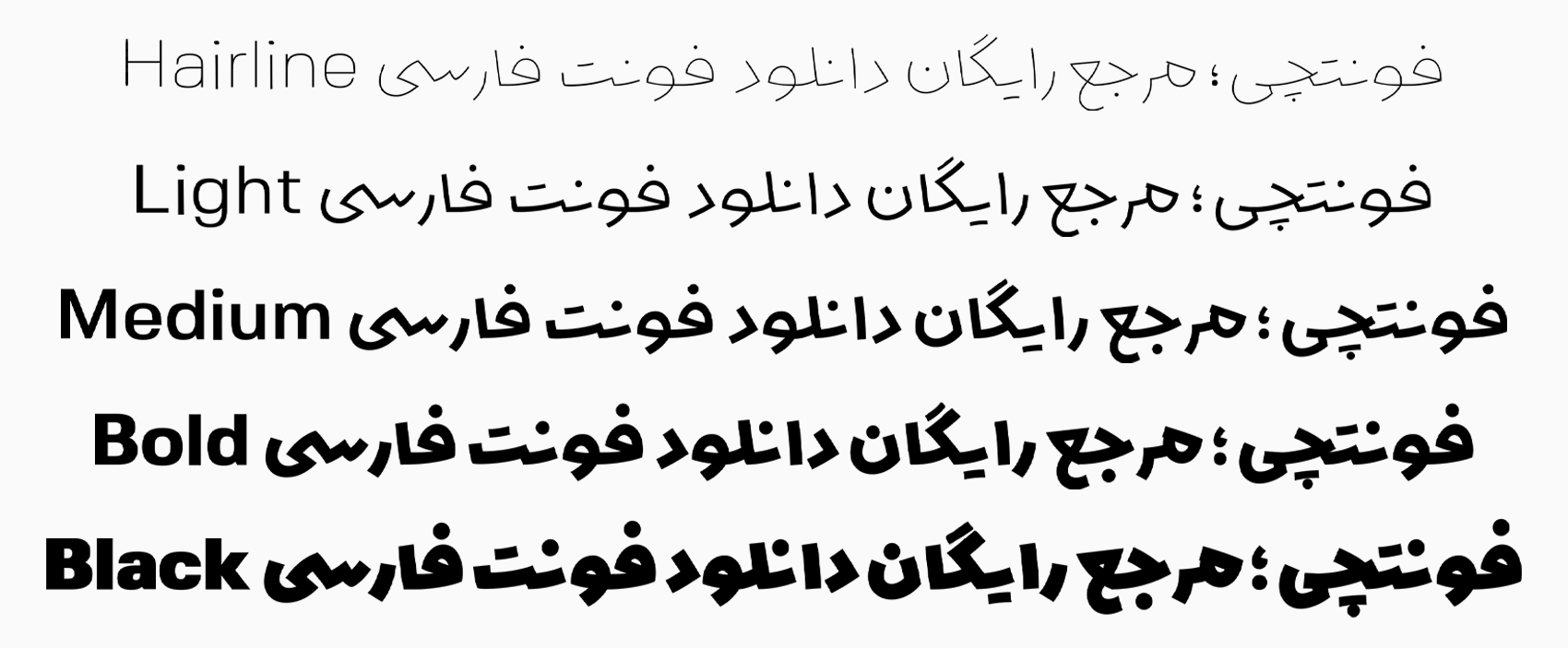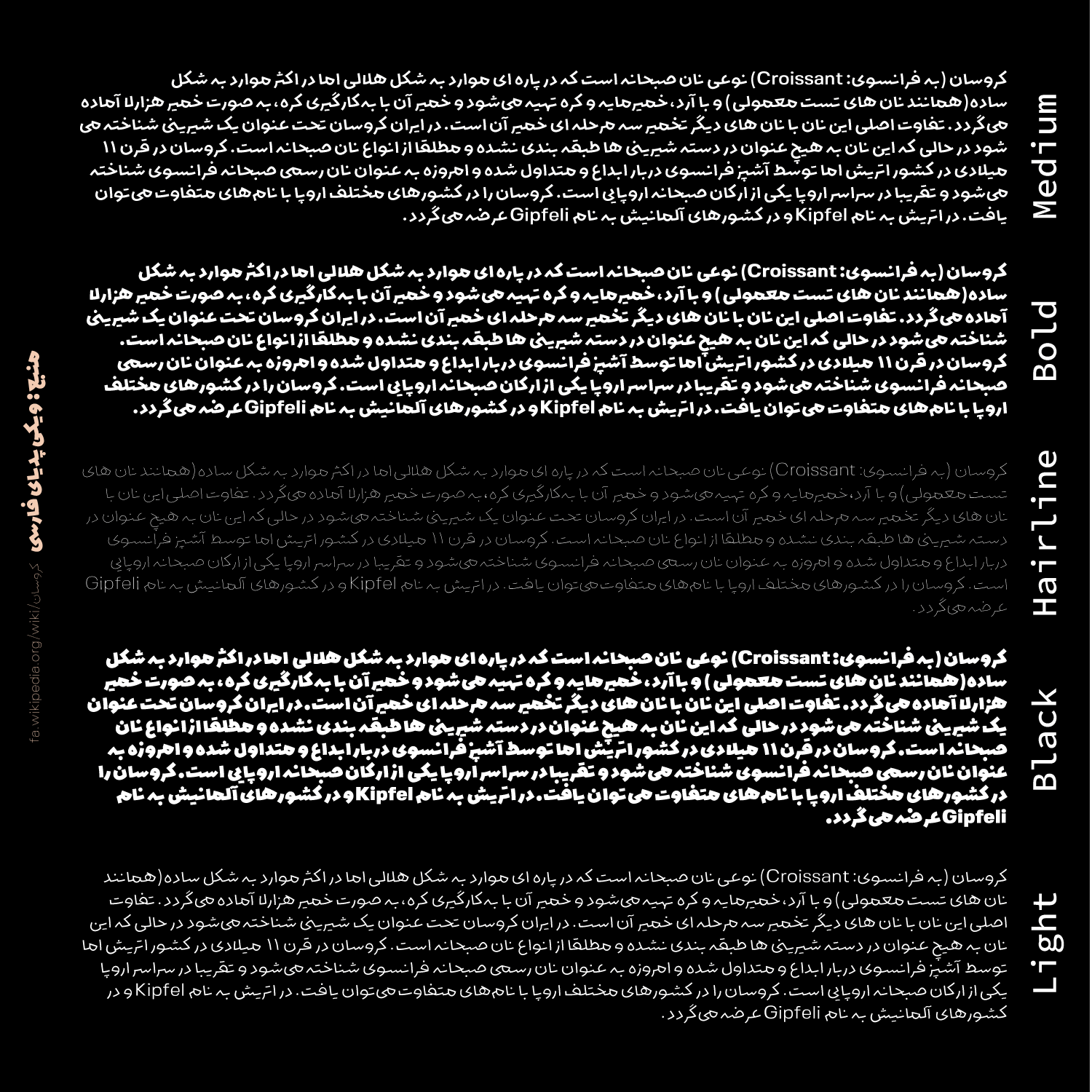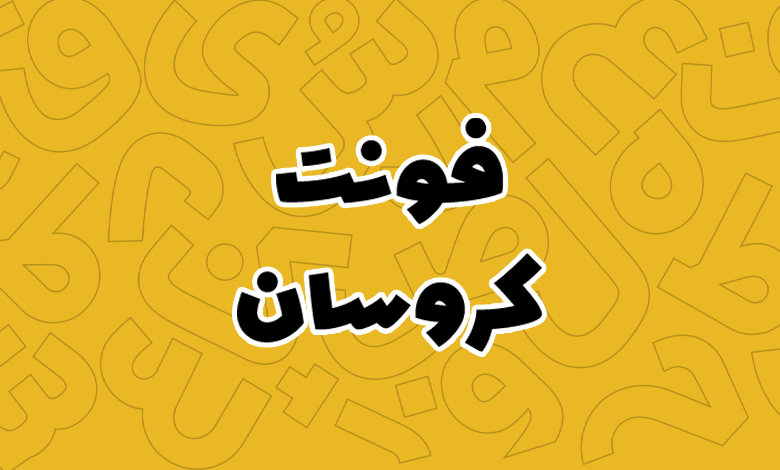
فونت کروسان (Croissant)
فونت کروسان (به انگلیسی: Croissant) از فونتهای جذاب و مدرن جدید با ساختاری هندسی است که با طراحی منحصربهفرد خود میتواند گزینهای ایدهآل برای استفاده در پروژههای متنوعی که با هدف فونت عناوین، بستهبندی محصولات و تبلیغات به آن نیاز داشته باشید مورد استفاده قرار گیرد. فونت کروسان رایگان نیست و در ۵ وزن مختلف در قالب دو بسته نرمافزاری ارائه شده است.
طراح فونت کروسان علی پزشک است که پیش از این فونت سینما را در سال ۱۳۹۵ طراحی نموده است. فونت کروسان نیز با همان سبک کلاسیک و قدیمی این خط طراحی شده است که در ادامه بیشتر به بررسی و معرفی این قلم خواهیم پرداخت.
بررسی و دانلود فونت کروسان فارسی (croissant)
فونت کروسان (Croissant) یک فونت چندمنظوره با طراحی مدرن و هندسی است که توانسته تعادلی زیبا میان سنت و نوآوری ایجاد کند. پشتیبانی از سه زبان، تنوع وزنی و اعداد فارسی حرفهای از جمله ویژگیهایی هستند که این فونت را به گزینهای محبوب برای طراحان تبدیل کردهاند.
ظاهر این فونت کلاسیک بوده و به طراحی حروف پیش از سال ۵۷ برمیگردد که عموما از این سبک فونت برای پوسترهای سینمایی و طراحی تابلوهای سردر واحدهای تجاری مورد استفاده قرار میگرفت.
با توجه به کاربردهای گستردهای که دارد، فونت کروسان یک انتخاب ایدهآل برای پروژههای دیجیتال و تبلیغاتی است که در ادامه بیشتر با آن آشنا خواهیم شد.
سبک طراحی و وزن فونت کروسان
کروسان با بهرهگیری از ساختار هندسی و فرمهای ساده، تعادل بین سنت و مدرنیته را بهزیبایی برقرار کرده است. این فونت در ۵ وزن مختلف ارائه شده که عبارتند از:
- Hairline: مناسب برای طراحیهای ظریف و مینیمال.
- Light: مناسب برای متنهای کوتاه با ظاهری ملایم.
- Medium: وزن تعادلی برای استفادههای عمومی در متون بلند.
- Bold: برای عناوین برجسته و جذاب بین متون بلند.
- Black: قدرتمند و جسور برای استفاده در عناوین همچون پوسترها و کارهای تبلیغات.
تنوع در وزنها، انعطافپذیری بالایی به این فونت بخشیده و آن را برای انواع استفادهها از لوگوتایپ گرفته تا عناوین پوسترها مناسب کرده است.
هر یک از این وزنها شخصیت خاص خود را دارند که برای استفاده در محیطهای مختلف ذکر شده میتواند این خط ره بهشکل ویژهای نمایش دهد. تمامی وزنهای پنجگانه این قلم با فرمتهای TTF, WOFF و WOFF2 ارائه شده که برای استفاده در انواع نرمافزار و فضای وب قابل استفاده است.
پشتیبانی از ۳ زبان متنوع
به لطف فارسی بودن فونت کروسان، این قلم برای استفاده در سایر زبانهای خاورمیانهای همچون عربی نیز قابل استفاده است. با اینکه تمرکز در نسخههای اولیه جدا از زبان فارسی روی عربی است، اما میتوانید برای سایر زبانها همچون کوردی و اردو که دارای ظاهر یکسان در حروف هستند نیز از این خط بهره ببرید.
این فونت با چینش استاندارد اعراب و نشانهگذاری روی حروف، جان تازهای به واژههای شما خواهد بخشید. بهخصوص در وزنهای بالا که در عناوین مورد استفاده قرار گیرد و با هدف تمرکز روی محیطهای تبلیغاتی، نگاه بیننده را بقاپد.
فونت انگلیسی croissant دیگر زبان پشتیبانی شده این خط است که روح دورانی فرهنگ سنتی ایران بهطور جدی با غرب درگیر شده و داد و ستدی را در این بین با گویش جدید نوشتاری شکل داده است.
این ساختار فونت croissant را برای پروژههایی که به تطبیق چندزبانه نیاز دارید، ایدهآل کرده است. کاراکترهای فارسی با دقت بالایی طراحی شدهاند و برای ایجاد هماهنگی در متون لاتین، از فونت FivoSans (با طراحی الکس اسلوبژنینوف) بهره برده که جلوهای یکپارچه و هماهنگ ارائه میدهد.
پشتیبانی از اعداد فارسی حرفه ای
دیگر ویژگی فونت کروسان پشتیبانی حرفهای از اعداد فارسی و عربی است. با توجه به تنظیم زبان صفحه کلید، اعداد استاندارد هر زبان تایپ خواهند شد. برای زبان عربی اعداد استاندارد «۴۵۶» و برای زبان فارسی نیز اعداد استاندارد «۴۵۶» تایپ میگردد.
انتظار میرود در آپدیتهای بعدی این قلم شاهد افزوده شدن فایل فونت مخصوص اعداد هک شده فارسی و همچنین نسخه بدون حروف لاتین باشیم تا برای استفاده نرمافزاری ساختاری حرفهایتر در اختیارمان قرار دهد.
فونت رایگان کروسان مناسب تبلیغات و عناوین
کروسان بهعنوان یک فونت جدید، امکاناتی فوقالعاده برای طراحیهای تبلیغاتی، پوسترها و عناوین ارائه میدهد. فرمهای نرم و روان این فونت باعث خوانایی بیشتر و جلب توجه نگاه مخاطب شده است. این ویژگیها، آن را به گزینهای بیرقیب در دنیای طراحیهای دیجیتال و چاپی تبدیل کردهاند.
در فضاهای دیجیتال و محیطهای شهری میتوانید از وزنهای این قلم بهصورت حرفهای استفاده کرده و ظاهر خیرهکننده و جذابی را به متون فارسی و عناوین خود بدهید. این سبک طراحی در فونت کروسان، بهویژه در عناوین کوتاهی که نشان از نام برند یا محصول داشته باشند، بهخوبی روی جذب نگاه مخاطب تاثیر خواهد گذاشت.
از دیگر کاربردهای فونت کروسان میتوان به استفاده در فضای کتاب اشاره کرد؛ خصوصا برای استفاده بر روی جلد کتاب که شامل عنوان آن باشد. چنین فونتی برای عنوان کتاب میتواند روی جذب مخاطب تاثیرگذار بوده و شانس خرید کتاب را هم بالاتر ببرد. بهویژه زمانی که همراه با یک طراحی منحصربهفرد بصری باشد.